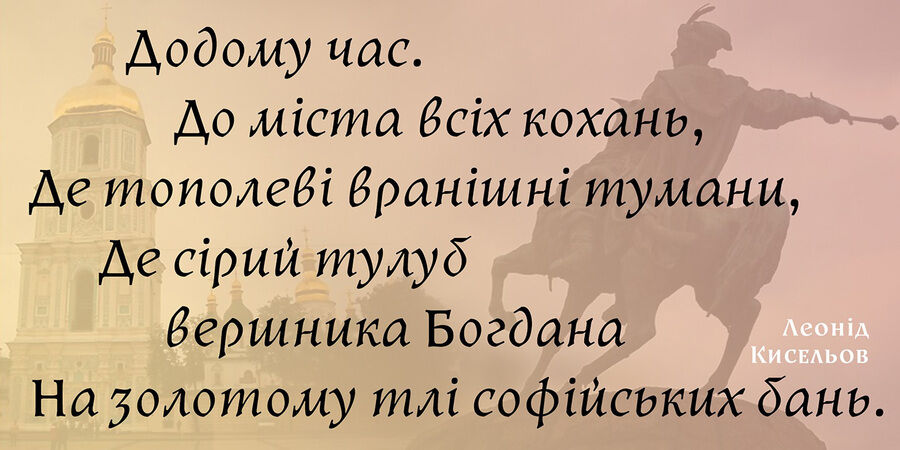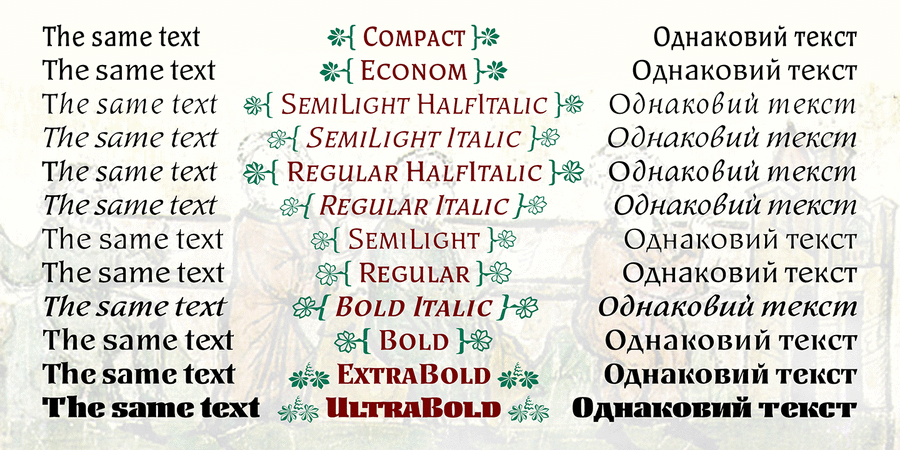
Шрифт Київ – це спроба об'єднати старостильну антикву з українськими традиціями й сучасними вимогами. Крім звичайного курсиву, додано традиційне для ренесансу «півкурсивне» накреслення. Також у шрифтове сімейство входять компактні накреслення. Особливий шарм додають декоративні мотиви каштанового листя й квітів у вигляді Флеронів. Також включені наджірні накреслення, щоб пристосувати шрифт до рішення різних дизайнерських завдань, як текстових, так і акцидентних. Київ був нагороджений в категорії текстових шрифтів на першому українському конкурсі шрифтів Ruthenia у 2010 році. Шрифт розробив Віктор Харик у 2010-2016 роках.
Асоціації з сімейством шрифтів KyivОсобистість і характер гарнітури:
старовинний, історичний, казковий, майстерний, художній, благородний, красивий, виразний, характерний, прекрасний, гуманітарний, динамічний, фантастичний, сріблястий, срібний, витончений, дорогий, розкішний, елітний, гострий, різкий, чіткий, консервативний, самобутній, оригінальний, етнічний, натуральний, традиційний, гордий, колоритний, артистичний, героїчний, племінний, ювелірний, дзвінкий, вишуканий, пафосний, аристократичний, якісний, осінній, музичний, культурний, освічений, легендарний, старомодний, лицарський, святковий, біблійний, християнський, церковний, релігійний, сакральний, різдвяний, ритмічний, живий, темпераментний, активний, поетичний, золотий, сильний, помітний, яскравий, монументальний, твердий, хоробрий, бравий, мужній, мотивуючий, амбітний, добротний, стійкий, ностальгічний, ремісничий, крафтовий, переконливий, впевнений, солідний, рукотворний, тісний, кам'яний, артізанальний, важкий, пузатий, товстий, екстравагантний, химерний, величезний, демонстративний, спекотливий, спекотний, багатий, претензійний, грандіозний